ハーゲンダッツという言葉自体に深い意味などない
ハーゲンダッツという如何にもグーデンベルクを連想される言葉だが、言葉自体に深い意味はないようだ。創始者であるルーベン・マッタスが、アイスクリームはデンマーク産というイメージがあるからとコペンハーゲンの「ハーゲン」とその余韻がマッチする「ダッツ」を組み合わせて作り出した造語になっている。
また米国の消費者にヨーロッパ風だという先入観を持たせるため、ヨーロッパの伝統と職人技を連想させるためにこの名前になったそうだ。さらに印象を強くするために創始者のマッタスは、デンマークの国土の一部の形を会社のロゴに取り入れている。
文字にもヨーロッパを想起される様に「ä(ウラムルト)」というゲルマン語の文字に使用される記号が使用されている。
ロゴを縁取る波形は「カトゥーシュ」と呼ばれる古代エジプトの文字で、その中に入っているものを「守る」という意味があり、ハーゲンダッツという大切なブランドをカトゥーシュで囲んで守るという意味をこめてデザインされている。
ダッツでいいならダッチでもゲッツでも良かった気がするがハーゲンダッチだったりハーゲンゲッツだったら今ほど高級感は生まれていなかっただろう。
スーパー猛暑は和のアイスで吹き飛ばせ!『ハーゲンダッツ クリスピーサンド「ほうじ茶 和の菓(わのか) ~黒糖仕立て~」』が7月に期間限定新発売
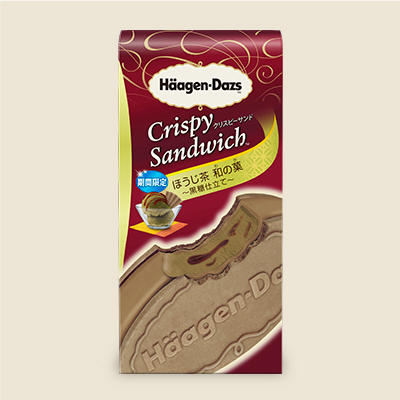
『ハーゲンダッツ クリスピーサンド「ほうじ茶 和の菓(わのか) ~黒糖仕立て~」』
ハーゲンダッツ ジャパンから『ハーゲンダッツ クリスピーサンド「ほうじ茶 和の菓(わのか) ~黒糖仕立て~」』が2018年7月10日(火)より期間限定で新発売される。
クリスピーサンド『ほうじ茶 和の菓(わのか) ~黒糖仕立て~』は、黒糖ソース入りのほうじ茶アイスクリームを、黒糖ほうじ茶コーティングで包み込み、サクサクとしたほうじ茶ウエハースでサンド。芳醇に香るほうじ茶とコク深い黒糖が織り成す、和スイーツならではの味わいが楽しめる。
梅雨が終わる頃に、清涼感あふれる爽やかさで『ハーゲンダッツ ミニカップ「甘夏」』が6月末に期間限定新発売
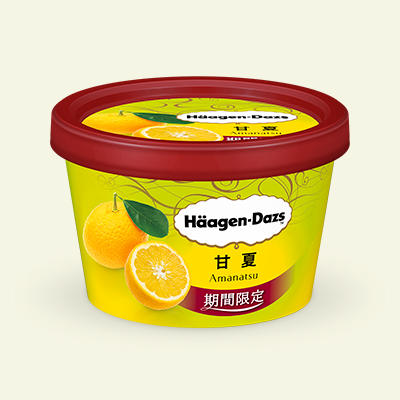
ハーゲンダッツ ジャパンから『ハーゲンダッツ ミニカップ「甘夏」』が2018年6月26日(火)より期間限定で新発売される。
ハーゲンダッツ ミニカップ「甘夏」は甘夏の風味を生かした優しい甘さとミルクのコクが味わえる甘夏アイスクリームに、かんきつ特有の爽やかな香りとほのかな苦みがアクセントとなる甘夏ソースを加わり、濃厚ながらも甘夏本来の爽やかでみずみずしい味わいが楽しる一品。
『ハーゲンダッツ 華もち「栗あずき」』を食べてみた
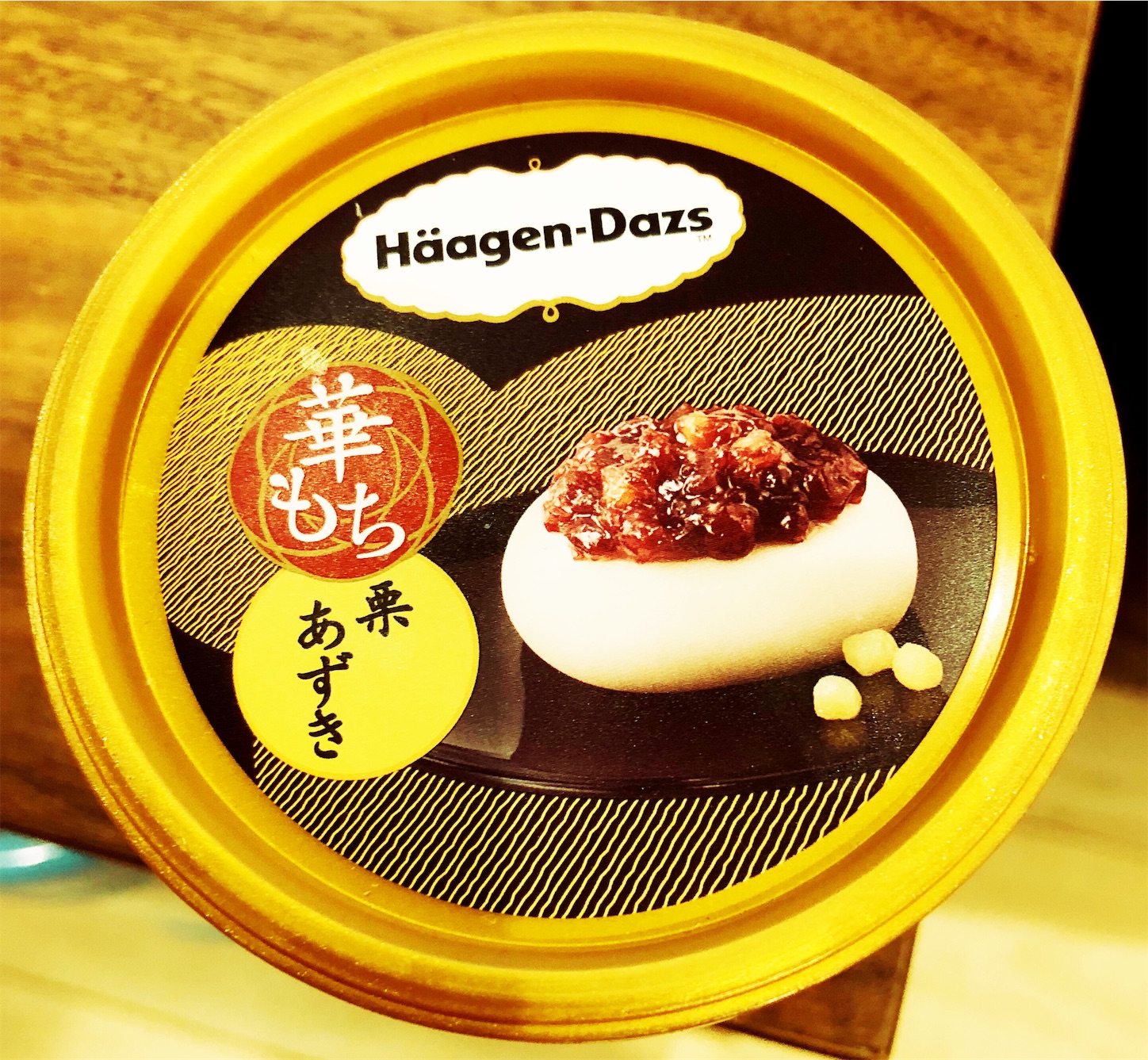
2018年2月27日から期間限定で発売した『ハーゲンダッツ 華もち「栗あずき」』『ハーゲンダッツ 華もち「桜あん」』が最近、スーパーやコンビニが在庫処理としてセール品に出されているのをよく見かける。そこで無類のあずき好きとして「栗あずき」を1つ購入してみた。割とおもち感はあり、美味い。
『ハーゲンダッツ 華もち「栗あずき」』『ハーゲンダッツ 華もち「桜あん」』が期間限定新発売!
ハーゲンダッツの新製品として『ハーゲンダッツ 華もち「栗あずき」』『ハーゲンダッツ 華もち「桜あん」』が2018年2月27日(火)より期間限定にて全国で新発売された。
ハーゲンダッツ 華もち「栗あずき」
華もち「栗あずき」は、アイスクリームの滑らかな口当たりと粒あんの食感が、絶妙なバランスを生み出しており、甘みが強く食感のある栗と、ふっくら炊き上げた小豆粒をもちの上に盛りつけられた。「栗ぜんざい」を表現した上品な見た目が、ふたを開けた瞬間から食欲をそそる。北海道産小豆の豊かな風味が際立つ小豆アイスクリームには、隠し味に黒糖を加え、深みのある上品な甘さに。中に入れた栗ソースは、栗そのものをすりつぶしたような食感で、素材の風味をダイレクトに感じられる。
ハーゲンダッツ 華もち「桜あん」
華もち「桜あん」は、春の和菓子として人気の高い「桜もち」の味わいを表現。桜の素材をアイスクリームやソース、あんに合わせて使い分けて桜の風味が口いっぱいに広がるようなフレーバーに仕上げられた。梅酢に漬けた桜の花を使った甘酸っぱいソースをもちの上にかけている。ふたを開けると目に飛び込んでくるピンク色のソースと上品な桜の香りは、春にぴったりの華やかさ。アイスクリームにはコクのあるミルクと桜の葉パウダーを合わせている。塩漬けした桜の花びらペーストと桜の葉パウダー入りの桜あんのほのかな塩味がクセになる味わい。